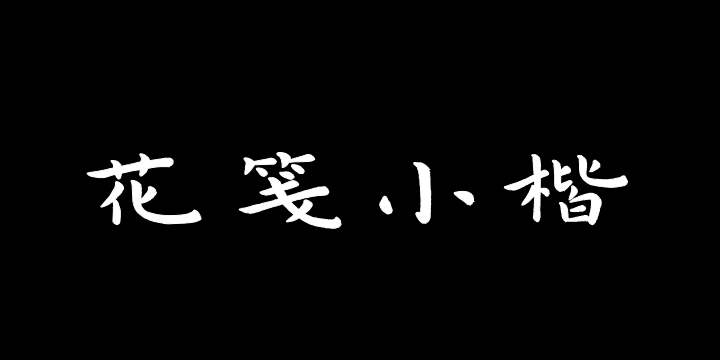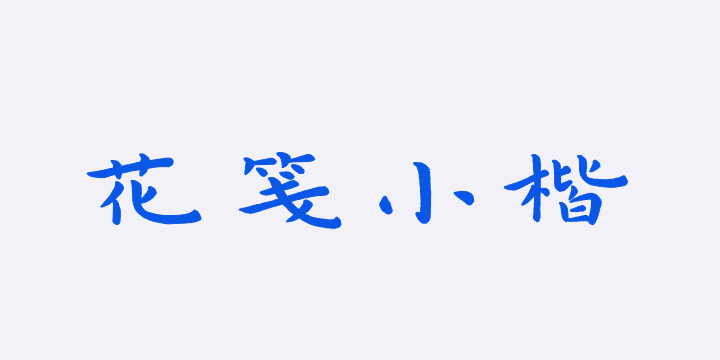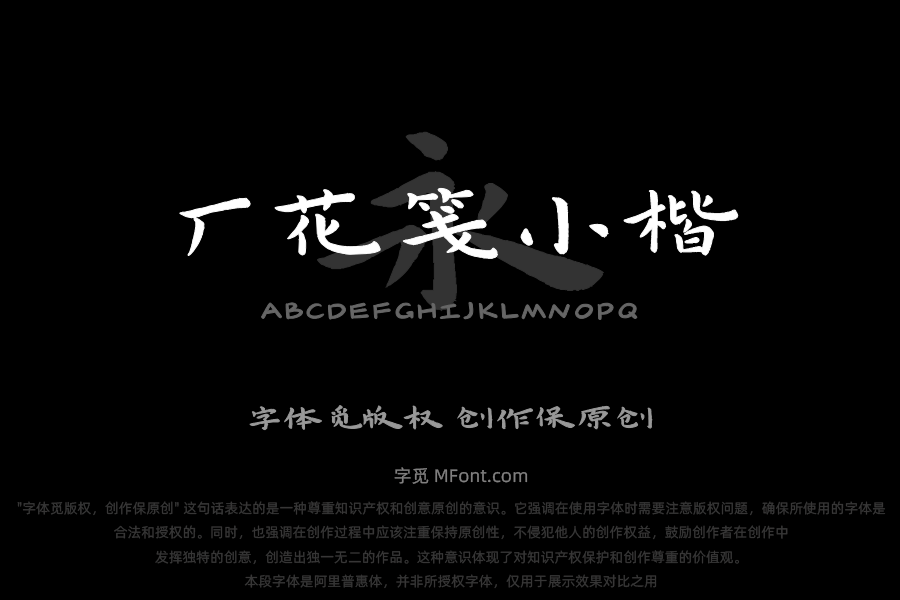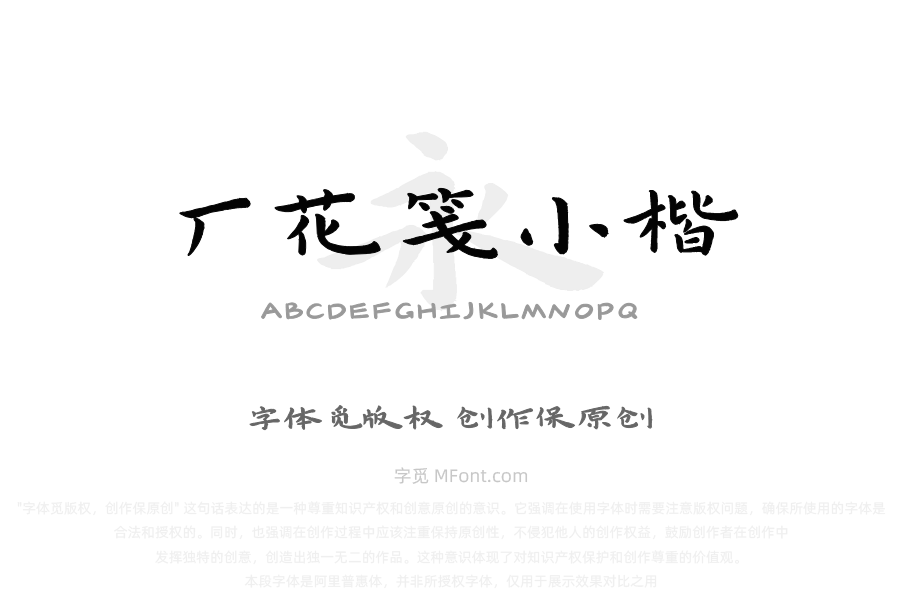
字体全名: 也字工厂花笺小楷
设计师: 也字工厂
字体简介: 这套字体取法自王宠《南华真经》和钟繇《宣示表》,二者都属于带有朴拙气质的小楷作品。相比于其它大开大合或风骨独特的书法字体,花笺小楷更像一款介于中间的字体。有魏晋时代舒朗的间架结构,亦糅合了明清时代书卷气的点画特征,轻巧又不轻佻,朴素又不泯然于众,给人以朗月清风的观感。